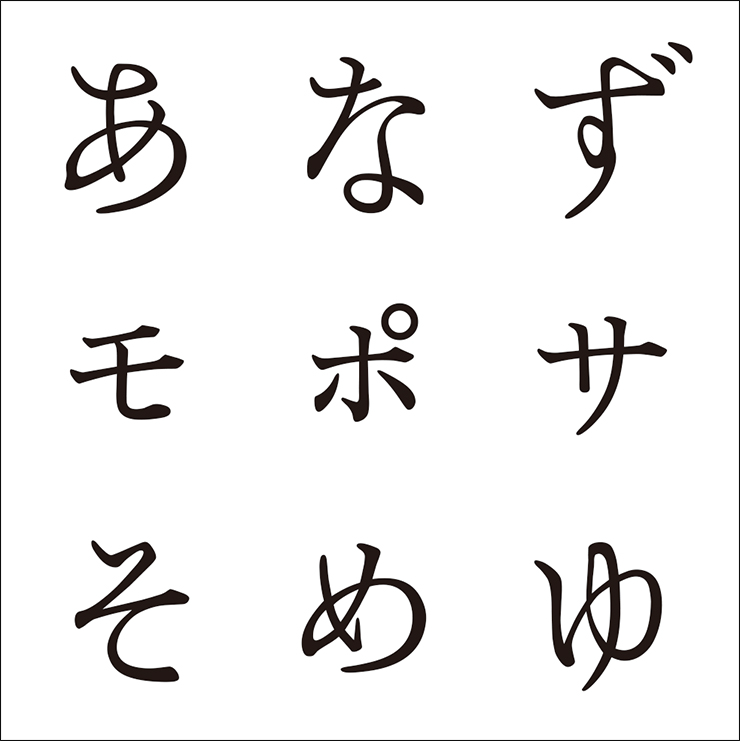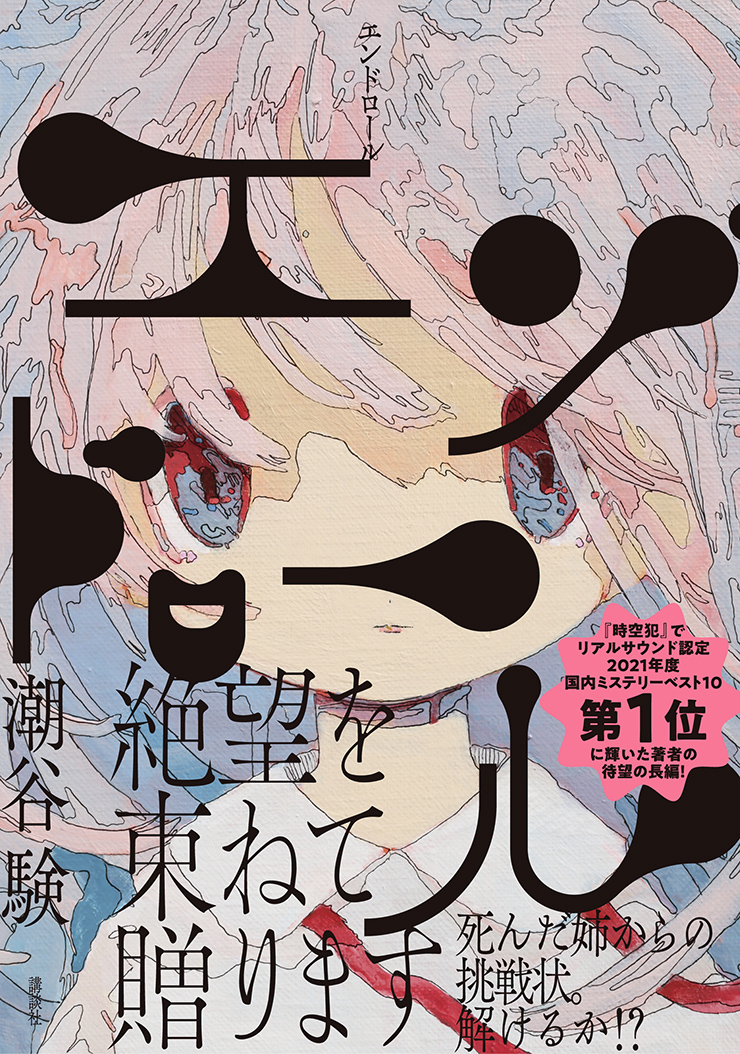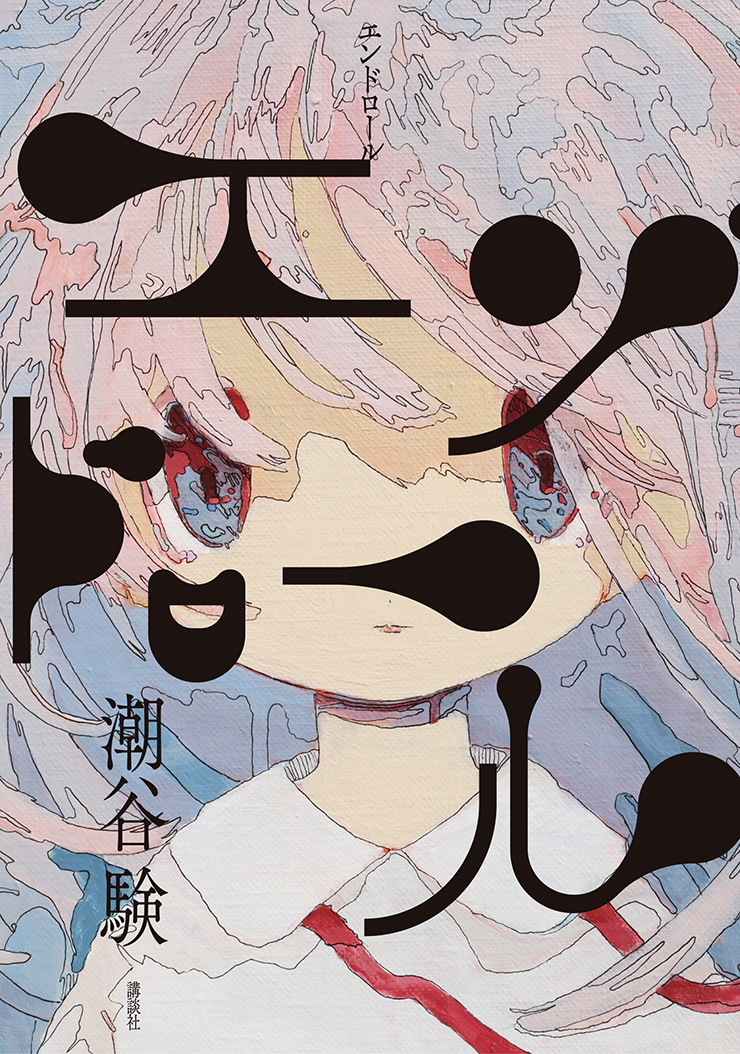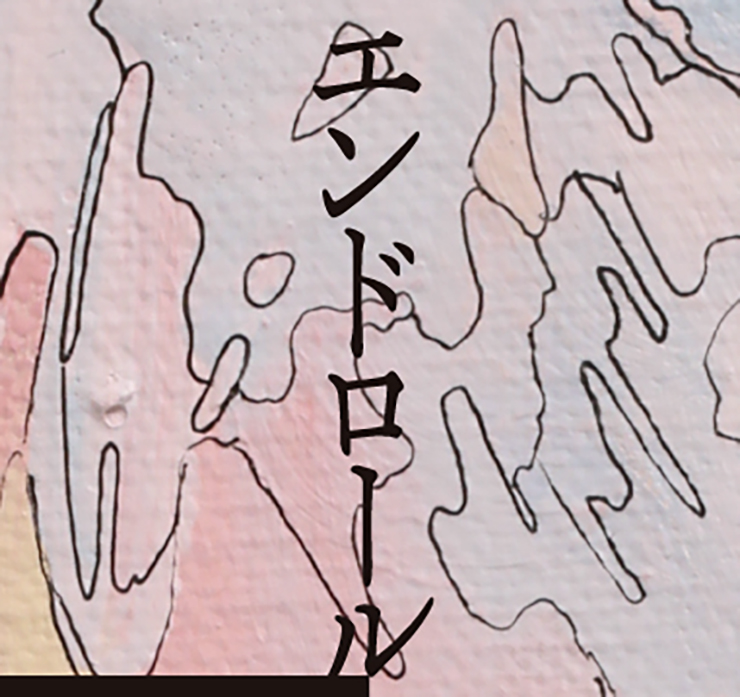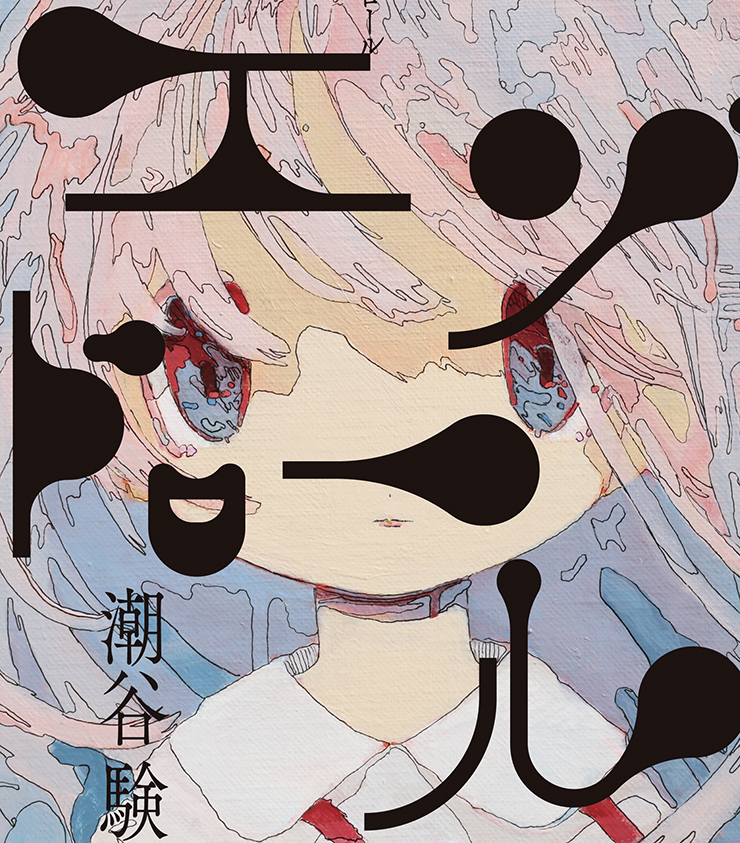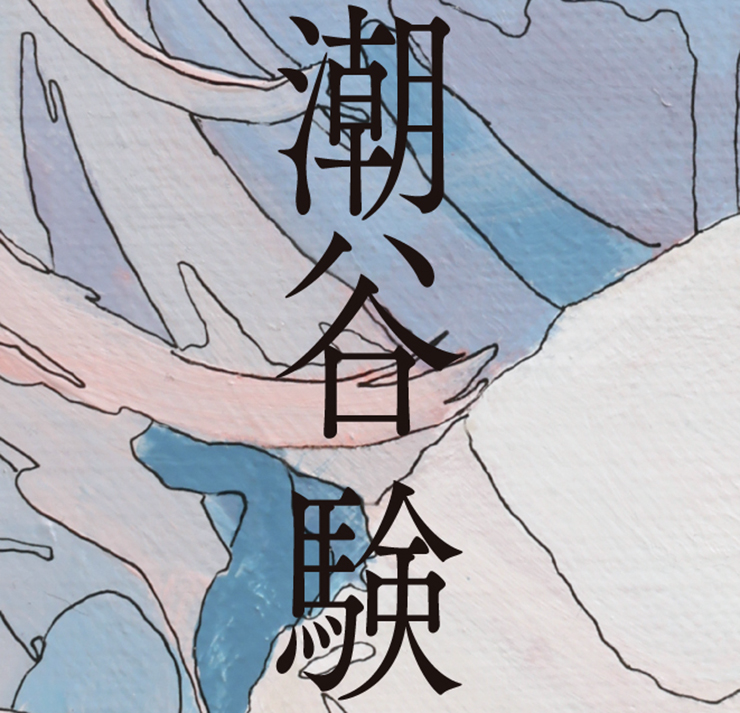
今回は書籍『エンドロール/潮谷験』(講談社)の使用フォントを解説。ブックデザインを手がけたtobufuneの奈良岡さんに取材しました。
遊び心のある文字で茶目っ気を感じさせつつ不穏な雰囲気に
新型コロナウイルスが蔓延する世界を舞台に、行動制限などの影響により不利益を被った若者たちの間で急増する自死と、それを巡る謎、死を望む若者の増加を阻止しようとする主人公の姿を描いたミステリー小説『エンドロール/潮谷験』。第63回メフィスト賞を受賞した『スイッチ 悪意の実験』や、リアルサウンド認定2021年度国内ミステリーベスト10の第1位に選ばれた『時空犯』などで知られる著者の長編第3作で、現実の社会情勢と予測不能の謎解きミステリーを融合した意欲的な作品になっている。
表紙カバーでは、その謎めいた作品世界が、どこか不穏な空気が漂う装画やグラフィカルなタイトルロゴなどで印象的に表現されている。デザインを担当したtobufuneの奈良岡さんによると「表紙カバーでは、作品の不穏な雰囲気を出したいと思いました。ただ読者層が比較的若い世代なので、不穏なだけでは終わりたくなく、ポップで茶目っ気のある感じも表現するよう心がけました。さめほしさんの装画も表現したかった雰囲気にガッチリとハマっていて、とても素敵なカバーにできたのではないかと思います」とのことだ。
Font.01「オリジナル」
遊び心あふれる文字で大胆かつキャッチーに
装画の上に大きくあしらわれたタイトルロゴ「エンドロール」部分は、カバーデザインのコンセプトに合わせて作り起こされたオリジナルの文字。単純な線を引いて骨格を設計したあと、バランスを見ながら装飾を加えたり、配置やフォルムを調整するなどして制作された。上図はその制作工程。
奈良岡さんによれば「『エンドロール』は比較的ポピュラーな言葉で、パッと見て認識しやすい文字でもあるため、形で遊んでもいいかなと思いました。そこで装画の魅力が引き立つよう気をつけながら作字しました。絵の上(しかも人物の顔の上)に大胆に文字を乗せるのは緊張感が伴いますが、その文字がうまくハマったというか、居所を見つけたときの喜びは何ものにも代えがたいですね。見た人の心に引っかかって『なんだかあの文字が気になるな』と思ってもらえたら嬉しいです」とのことだ。
Font.02「かもめ」
タイトルとコントラストをつけて画面を引き締める
表紙カバー上部の縦書きの「エンドロール」部分や帯のかな部分は、タイプデザイナーの今田欣一氏によるシャープな印象のかな書体「かもめ」(欣喜堂)に。昭和18年に発行された『内閣印刷局七十年史』の本文に用いられている伝統的な和字書体を復刻したもので、欣喜堂の提携先のモリサワからは古典的な宋朝体「龍爪」の漢字と組み合わせた「かもめ龍爪」としてリリースされている。
奈良岡さんによれば「タイトルロゴが紙面で踊っている印象なので、画面を引き締めるため、それ以外の文字はシャープな書体を選びました。若干長体をかけることで、より緊張感を出す工夫をしています」とのこと。
Font.03「筑紫オールド明朝 R」
伸びやかで美しいデザインの明朝体に
著者名や帯の漢字部分の文字は、力強い打ち込みや伸びやかなハライなどが特徴的なオールドスタイルの明朝体「筑紫オールド明朝 R」(フォントワークス)に。タイトルロゴと差別化して画面を引き締めるため、シャープな印象の明朝体が選択された。縦書きのメインタイトル部分と同様に、緊張感を出すため若干長体をかけて使用されている。